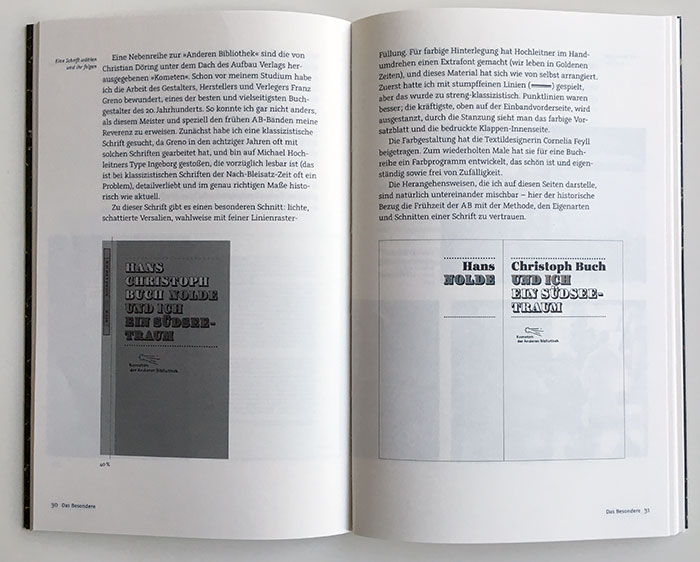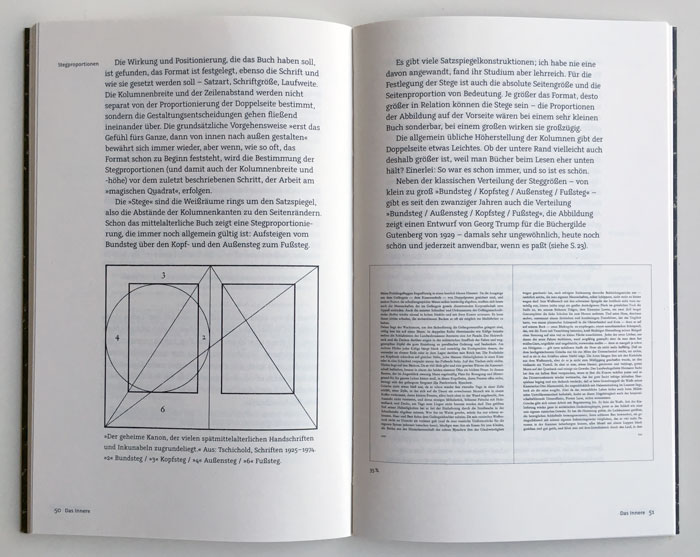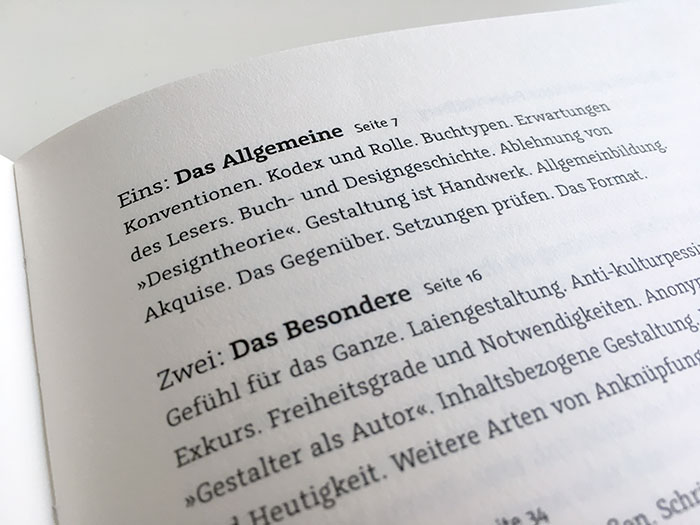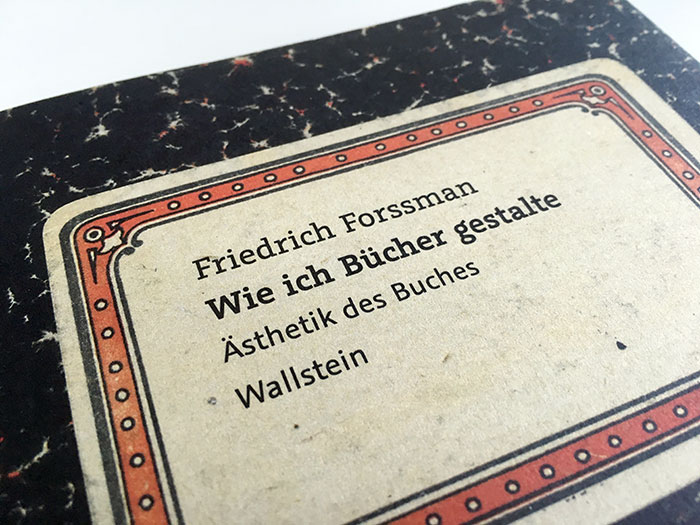
Wie ich Bücher gestalte
Noch vor zwanzig Jahren gab es in jedem größeren Verlag nicht nur eine ganze Abteilung für die Buchentwürfe, sondern auch einen Künstlerischen Leiter, der für einen möglichst hohen Entwurfsstandard und besonders schöne Bücher sorgte. Mancher trug einen langen weißen Seidenschal, damit man ihn gleich erkannte. Heute sind nicht nur die Seidenschalträger verschwunden, es gibt in den Verlagen gleich gar niemanden mehr, dessen Arbeit ausschließlich darin besteht, Büchern ein schönes Gewand zu geben. Die verlagseigene Buchästhetik wurde zur Verschwendung erklärt und ausgelagert. Damit haben sich die Verlage auch der Sachverständigkeit entledigt, Schönheit im Buch überhaupt zu erkennen. Die Kriterien für ein gut hergestelltes Buch liegen in den großen Verlagen heute weitgehend im Dunkeln, das technische Vokabular ist nur noch rudimentär vorhanden. Grafikdesign- und Werbeagenturen werden mit der Druckvorlagenproduktion beauftragt, Handelsagenten entscheiden über die Umschläge nach Marktüberlegungen, und die wichtigsten Kriterien für die Auftragsvergabe bestehen in Preis und Geschwindigkeit. Und so sehen die meisten Bücher aus: außen bunt, innen beliebig und insgesamt lieblos gemacht.
Es gibt aber Ausnahmen. Wenn der Buchgestalter Friedrich Forssman bei Suhrkamp, Weidle, Reclam, zu Klampen oder dem Wallstein-Verlag auftaucht, wo nun ein Werkstattbericht über seine Arbeit erschienen ist, kommt der Seidenschal in die Bücherwelt zurück (»FF« hat ein bekanntes Monogramm, raucht Pfeife und fährt einen Oldtimer) und mit ihm die ganze herrliche Ausstattungskultur vergangener Zeiten in einer frischen Blüte.
Nun darf man nicht denken, hier werde einem Dandy gehuldigt. Friedrich Forssman war an zwei umfangreichen Standardwerken beteiligt, in denen das gesamte Handwerkswissen von Buchgestaltung und Schriftsatz, soweit das möglich ist, zusammengefaßt wurde und die stets in aktualisierten Auflagen lieferbar sind: »Lesetypografie« (1997, mit Hans Peter Willberg) und »Detailtypografie« (2003, mit Ralf de Jong). Als bedeutendste Referenz für seine Buchentwürfe und sein Können als Schriftsetzer dürften die Arbeiten für die Arno-Schmidt-Stiftung gelten, für die er seit 1990 alle Bücher und Drucksachen entwirft, namentlich »Zettel’s Traum«.
In seinem nun erschienenen Werkstattbericht von achtzig Seiten, einem von außen wie eine Kladde aussehenden Heft, wird klar, welchen Anspruch Forssman an seine Arbeit stellt und worauf sich Verleger, die schöne Bücher lieben, einlassen, wenn sie ihn mit Entwürfen beauftragen. Forssman irrt allerdings, wenn er meint, die Buchbranche sei »eine recht heile Welt«, deren Bewohnern er die Liebe zum Buch bescheinigt. Denn die meisten großen Verlage kann er damit kaum meinen. In seinem Essay gibt er über seine Haltung Auskunft. Forssman stellt klar, daß es in einem ausdiskutierten Entwurfskonflikt nur eine entscheidende Instanz geben sollte­­: »Wer dem Gestalter nicht vertrauen kann, ist kein guter Auftraggeber; wer als Gestalter wider besseres Wissen klein beigibt, ist kein guter Gestalter.« Dieser Standpunkt dürfte in behördenähnlich auf Konfliktfreiheit getrimmten Bestsellerverlagsstuben wenig Aussicht auf Verständnis finden; die kleineren Verlage profitieren aber davon, wenn sie den Buchentwurf und vor allem die Typografie als Unterscheidungsmerkmal etablieren.
Wie Friedrich Forssman aus einem Text ein Buch formt, wie er den Entwurf aus dem Text ableitet, um dem Leser einen Gegenstand in die Hand zu geben, dessen Gestalt als angenehm empfunden wird, beschreibt er detailliert und an Beispielen. Diesem praktischen und persönlich gehaltenen Teil des Aufsatzes ist der meiste Platz eingeräumt, so daß Lesern wie Verlagsleuten und auch dem Nachwuchs empfohlen werden kann, sich mit diesem Werkstattbericht einen erhellenden Zugang zur Arbeitsweise eines herausragenden Buchgestalters zu verschaffen. Forssman behandelt grundsätzliche Fragen wie die des Buchformates und stellt dar, wie er sich seine Position als interpretierender Diener des Textes schrittweise erarbeitet: in der Wahl der Schrift, der Beurteilung ihres Klanges, ihrer Abstimmung durch Größe, Zeilenlänge, Zeilenabstand und Einrichtung von Buchstaben- und Wortabständen. Die Druckschrift versetzt einen Text in eine charakteristische Stimmung, die dem Leser nicht als Mißklang auffallen darf; in den meisten Büchern darf er ihre Form gar nicht bemerken, weil nicht die Übertragung der Gedanken selbst wichtig ist, sondern der Text ohne Überwindung typografischer Barrieren in die Vorstellung des Lesers dringen, im Ton des Textes aber mitschwingen soll. Ebenso geht der Buchgestalter mit Papier und Farbe um, auch mit Bildern.
Für den typografischen Kenner ergibt sich bei der Lektüre auch Überraschendes: »Es gibt viele Satzspiegelkonstruktionen; ich habe nie eine davon angewandt, fand ihr Studium aber lehrreich.« Das ist ein beachtliches Statement für einen Buchgestalter, dem die Konvention im Buch so wichtig ist, weil er das Gewohnheitsrecht der Leser nicht nur respektiert, sondern zur vernünftigen Grundlage seiner Arbeit erklärt. Dabei wirkt auch das vorliegende Werk mit seinem wohlproportionierten Satzspiegel und den Marginalien im besten Sinne klassisch aufgebaut. Erklären läßt sich das mit dem Scharfblick eines Typografen, der sich seit seiner Jugend für Bücher und ihre Form interessiert und derart einen so sicheren Blick für Maßverhältnisse gewonnen hat, daß er keine Geometrie mehr braucht. Das vermögen nur wenige, und so klar und schön darüber schreiben gegenwärtig wohl niemand außer Friedrich Forssman.
Untertitel: Ästhetik des Buches
Autor(en): Friedrich Forssman